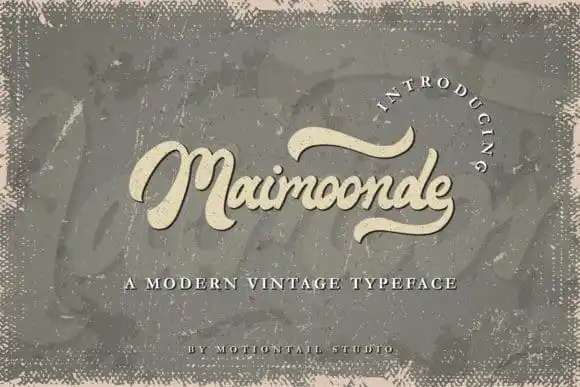
Maimoonde Bold Script Font – Download Grátis
Maimoonde Bold Script Font é uma elegante tipografia escrita, criada pela MotionTailStudio. Com seu estilo brilhantemente sofisticado e versátil, essa fonte será a escolha perfeita para qualquer projeto que você tenha em mente. Seu aspecto amigável tornará o texto inconfundível em uma variedade de contextos, do design gráfico ao design editorial ou até mesmo na marca personalizada. Esta fonte pode ser acessada facilmente com PUA (Paragraphs Underlining and Access), permitindo que você acesse todos os caracteres e adesivos sem nenhum problema. Experimente Maimoonde para dar um toque único e sofisticado ao seu próximo projeto de design.